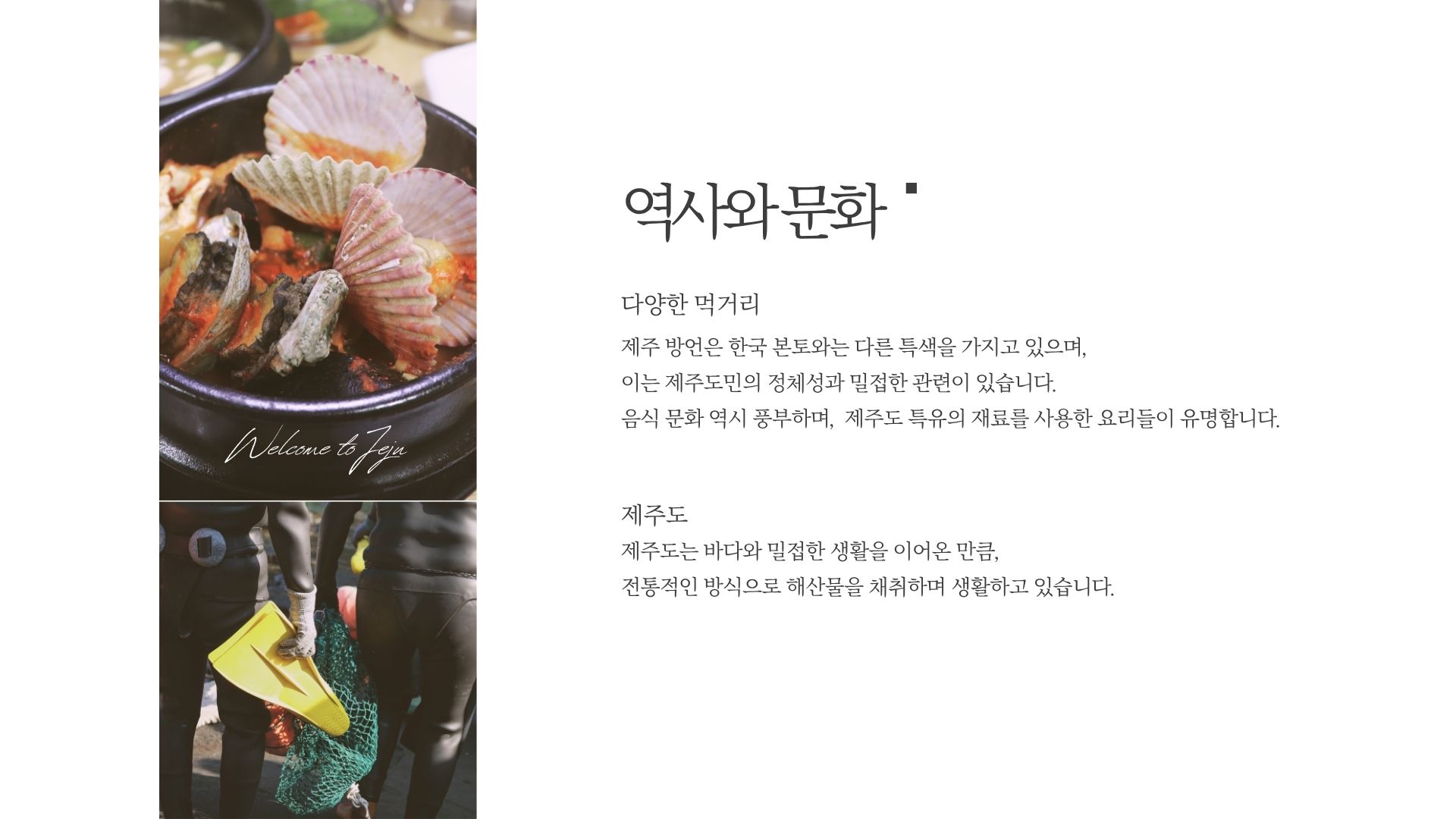
제주명조 — 제주도청에서 배포하는 무료 폰트입니다. 절제된 곡선과 넓은 속공간으로 시원하고 단정한 인상을 주는 명조체
제주특별자치도가 2010년에 공개한 제주서체 세 벌 가운데 부리가 있는 쪽입니다. 제주고딕, 제주한라산과 함께 나왔습니다.
만든 취지를 도가 밝혀 두었습니다. 제주의 상징성과 문화적 고유성을 살리고 국제도시로서 디자인적, 예술적 품격을 갖춘 문화예술의 이미지를 담은 미래 지향적 서체를 개발한다는 것이었습니다. 세 벌의 역할도 나뉘어 있어 한라산체는 안내표지판과 제목에, 고딕체는 디지털 화면에, 이 서체는 공문서와 인쇄물에 쓰도록 안내됩니다.
**이 서체의 존재 이유는 제주어입니다.** 제주대학교 국어문화원의 자문을 받아 아래아와 쌍아래아 같은 옛 글자를 넣었고, 제주어 160자를 지원합니다. 제주어를 표기할 수 있는 폰트가 거의 없다는 점에서 이 서체군의 값어치가 여기에 있습니다.
조형 설명은 고딕체와 묶여 있어 이 서체만의 서술은 따로 없습니다. 파일에서 재어 보면 획이 가늘어 자면을 채우는 비율이 낮은 편이니, 작은 크기나 저해상도 화면에서는 흐릿해질 수 있습니다. 굵기는 하나이고 현대 한글 11,172자를 모두 담았습니다. 맥에서는 OTF만 제공됩니다. 무료로 쓸 수 있고 유료 양도와 판매만 금지됩니다.